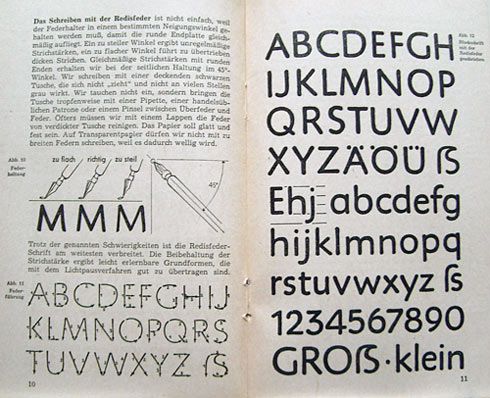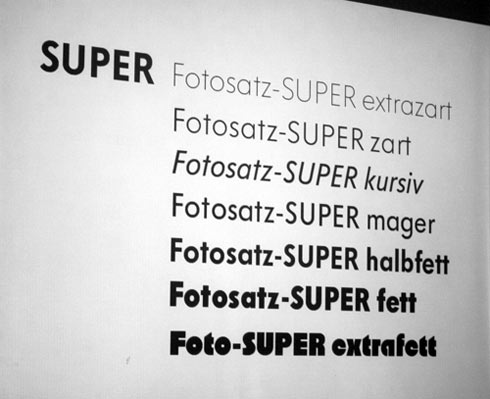
Ein Nachruf von Ivo Gabrowitsch
Karl-Heinz Lange lernte ich 2007 auf einem unserer ersten Typostammtische kennen. Kurze Zeit später lud er mich in seine Wohnung ein, um seinen ersten Vortrag, den er auf einer der folgenden Veranstaltungen zu halten gedachte, zu besprechen: »Körper und Stimme leiht die Schrift dem stummen Gedanken«. Anlass für diesen Vortrag war ein Jubiläum der besonderen Art. Lange blickte nämlich gerade zurück auf 60 Berufsjahre. 60 erfolgreiche Jahre des Gestaltens und Schriftentwerfens.
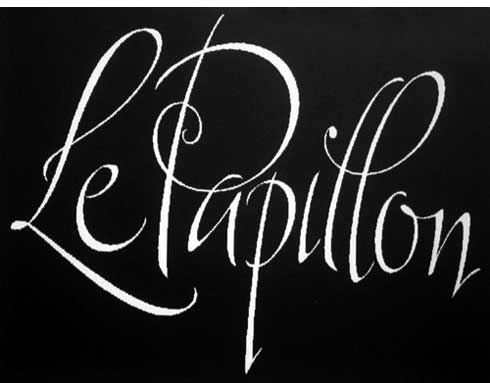
Meine Lieblingsarbeit von ihm: Plakat für das Ballett »Le Papillon« [Der Schmetterling] (© Foto Florian Hardwig)
In seiner mit zahlreichen Grafiken dekorierten Wohnung in Berlin-Mitte zeigte er mir Zeichnungen, die er bereits im Kindesalter anfertigte und sein Talent schon früh erkennen ließen. Er offenbarte faszinierende Arbeiten seines kreativen Schaffens, spielte am Klavier und erzählte genussvoll Anekdoten eines aufregenden Lebens. Eine handelte davon, wie er einmal von seinem Arbeitgeber VEB Typoart den Auftrag bekam, eine Schrift ähnlich der im Westen populären Optima von Hermann Zapf zu zeichnen.
Er übernahm den Auftrag, hoffte aber, dass sich seine eigene Handschrift ausreichend auf die Einzigartigkeit der Formen auswirken würde — schließlich war er eigenständiger Gestalter, kein Plagiator. Anlässlich einer Familienfeier durfte Karl-Heinz Lange nach Frankfurt/Main reisen. Dort traf er sich heimlich mit Zapf, um mit ihm seine Entwürfe zu diskutieren. Nicht ohne Stolz erinnerte er sich, wie sein westdeutscher Kollege sein Einverständnis gab und ihm gar großen Respekt für die geleistete Arbeit zollte. Die Publica war etwas völlig Eigenständiges geworden.
Karl-Heinz Lange an seinem Piano (© Foto Leslie Kuo, Pingmag)
Lange präsentierte mir an seinem Laptop vergnügt seine vorbereiteten Folien, nicht ohne dabei immer weitere Anekdoten zum Besten zu geben. Er lebte jedoch nicht in der Vergangenheit, sondern nahm immer wieder Bezug zum Hier und Jetzt und bekundete ernsthaftes Interesse am aktuellen Geschehen in der Typografieszene sowie an seinem Gast. Lange war intensiv darum bemüht, seine Schriften mit Hilfe jüngerer Kollegen wie zum Beispiel Ole Schäfer in die Zukunft zu retten.
Zum ersten Mal kam ich an diesem Tage mit seiner tiefen Leidenschaft zur Gestaltung von und mit Schrift in Berührung. Sie beeindruckte mich nachhaltig. Das war kein zartes Leuchten in den Augen eines in die Jahre gekommenen Mannes, das war ein Aufflammen in den Augen eines Kind Gebliebenen, das weiterhin die Welt erforscht. Aus einer geplanten Stunde wurde ein ganzer Nachmittag, der mich noch Wochen später beschäftigte. Sein Vortrag schließlich fesselte auch das Publikum auf magische Weise.
Karl-Heinz Lange und Erik Spiekermann im Oktober 2007 beim Berliner Typostammtisch (© Foto Andreas Seidel)
Wann immer der sympathische Gestalter konnte, bereicherte er unsere Veranstaltungsrunde mit seiner Anwesenheit, was ihm aufgrund seiner Gesundheit nicht immer leicht fiel. Lange war um einen ständigen intensiven Diskurs bemüht und genoss die Gemeinschaft von Gleichgesinnten, egal welchen Alters. Er begegnete ihnen respektvoll und interessiert.
Zirkus (© Foto Florian Hardwig)
Im vergangenen Jahr trat Karl-Heinz Lange mit einer außergewöhnlichen Bitte an mich heran: Anlässlich seines 80. Geburtstages wollte er nach Jahrzehnten der Hörsäle und Konferenzen gern seinen allerletzten Vortrag im Rahmen unserer typografischen Hauptstadtrunde halten. Der Besonderheit und der großen Ehre dieses Momentes bewusst nahmen an jenem Abend im August erstmals mehr als 50 Leute am Typostammtisch teil. Von ihnen bereute niemand die zum Teil weite Anreise. Beginnend mit seinen beschwerlichen Kinderjahren in Westpreußen ließ er sein ganzes aufregendes Leben Revue passieren. Er berichtete auf heitere Weise, wie er jahrelang im Harz eine schwere Tuberkulose kurierte und wie letztlich dort seine ersten künstlerischen Aktivitäten und schließlich die fortan niemals endende Liebe zur Schrift entbrannte.
Doppelseite des Lange-Buchs »Schrift: schreiben, zeichnen, konstruieren, schneiden, malen.« 1965, VEB E.A. Seeman Verlag Leipzig (© Foto Dan Reynolds)
Karl-Heinz Lange hat den visuellen Alltagsausdruck der DDR entscheidend mitgeprägt: vom Telefonbuch über zahlreiche Literatur und verschiedene Unternehmensauftritte. Zweifelsohne zählt der ehemalige Schüler Herbert Tannhaeusers zu den wichtigsten Schriftgestaltern der DDR. Als Beweis dienen auch für spätere Generationen seine Schriften:
Langes Neuzeichnung der Super Grotesk von Arno Drescher für den Fotosatz (© Foto Florian Hardwig)
- 1955 Diplom-Antiqua (bleibt leider unveröffentlicht)
- Seine Schriften für VEB Typoart:
- Bearbeitung der Bleisatzschriften Magna, Primus und Super Grotesk für Fotosatz
- Publica (1983, Silbermedaille »Bienale of Graphic Design Brno 1984«)
- Minima (1984, als Satzschrift für Telefonbücher und Gebrauchsanleitungen)
- Seine Schriften für Elsner+Flake
- Rotola (1985/2007)
- Viabella (2009)
- Seine Schriften für Primetype
- PTL Minimala (2009)
- PTL Publicala (2009, Fontwerk beste Schriften 2009)
- PTL Superla (2009)
Karl-Heinz Lange starb vergangenen Dienstag kurz vor seinem 81. Geburtstag, nach einem – wie er selbst sagte – erfüllten Leben. Die Trauerfeier findet am 16. Juli 2010 um 12 Uhr statt.
Ein beeindruckender Mensch und großartiger Typograph und Grafiker. Er wird mir fehlen …